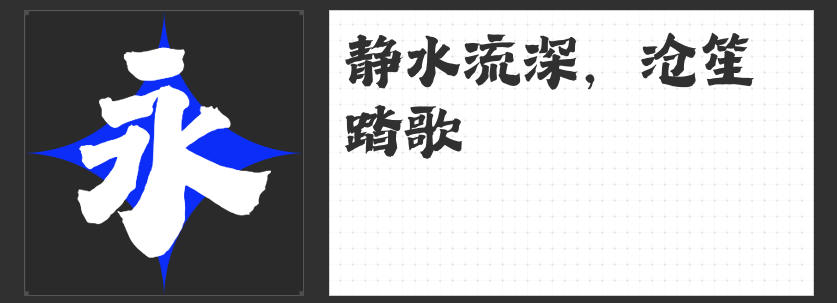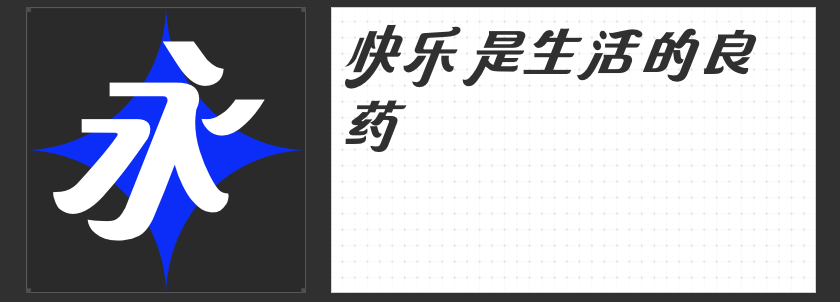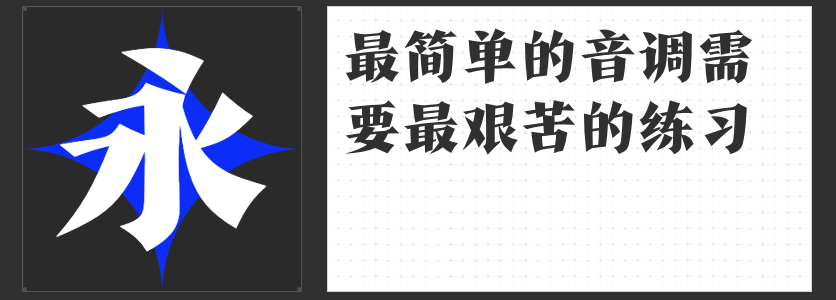
教师节宣传必备:四款独具特色的字体推荐
教师节即将到来,为了更好地表达对老师的敬意与感激之情,一份精美的宣传资料必不可少。而在这份资料中,字体的选择无疑是至关重要的环节之一。合适的字体不仅能够凸显主题,还能使整个设计更具吸引力。以下是四款适合用于教师节宣传活动的字体推荐,希望能帮助您打造出令人眼前一亮的作品。
1.字青春逐梦简 准粗
“字青春逐梦简 准粗”是一款充满活力的手写体,它不仅具备现代感十足的外观,还蕴含着积极向上的精神内涵。对于那些旨在展现教师对学生梦想支持与鼓励的宣传内容而言,使用该字体能够很好地呼应活动主题,激发起师生间的情感共鸣。
2.万人字造踏歌行体
如果您的宣传材料希望传达出一种浓厚的文化氛围,那么“万人字造踏歌行体”将是不错的选择。这款字体以古代诗词为灵感来源,融合了传统书法艺术与现代设计理念,给人一种书卷气十足的感觉。无论是用来撰写感谢信还是制作纪念册,“万人字造踏歌行体”都能为您的作品增添几分文艺范儿。
3.高手字斋东京体
“高手字斋东京体”以其简约明快的风格,在众多字体中脱颖而出。虽然形式上看似简单,但却不失细节处理上的精致考究。这样的字体非常适合用于需要强调文字内容本身重要性的场合,如教师节表彰大会邀请函或是感谢卡的设计。通过使用“高手字斋东京体”,可以让读者将更多注意力集中在文字所传达的信息上,达到更好的沟通效果。
4.造字侠郝刚快乐简 微黑
最后一个推荐给大家的是“造字侠郝刚快乐简 微黑”。这款字体采用了较为圆润的笔触设计,给人一种亲切、愉快的感觉。特别适合于那些想要营造轻松愉悦氛围的教师节活动策划。无论是制作班级活动海报还是校园广播稿,“造字侠郝刚快乐简 微黑”都能够以其独特的魅力,帮助传播正能量,增进师生情感交流。
通过以上四款字体的应用,相信您可以为即将到来的教师节创造出既美观又有意义的宣传作品。每一种字体都有其独到之处,关键在于如何根据具体需求和个人喜好来选择最适合自己项目的那一个。希望每位老师在这个特殊的日子里都能感受到来自学生和社会各界最真挚的祝福!